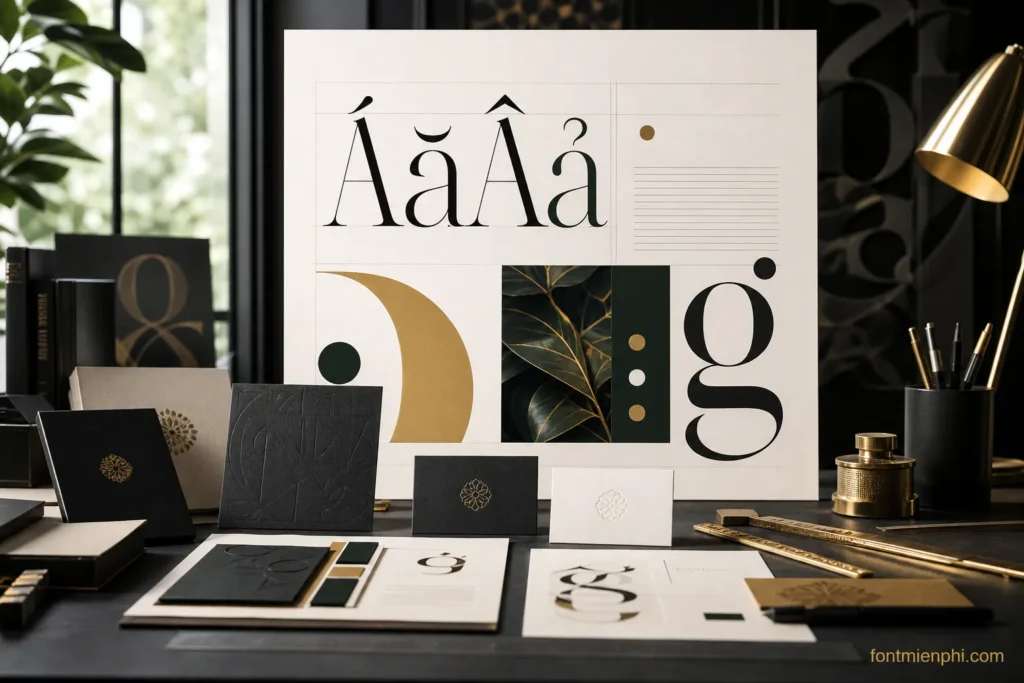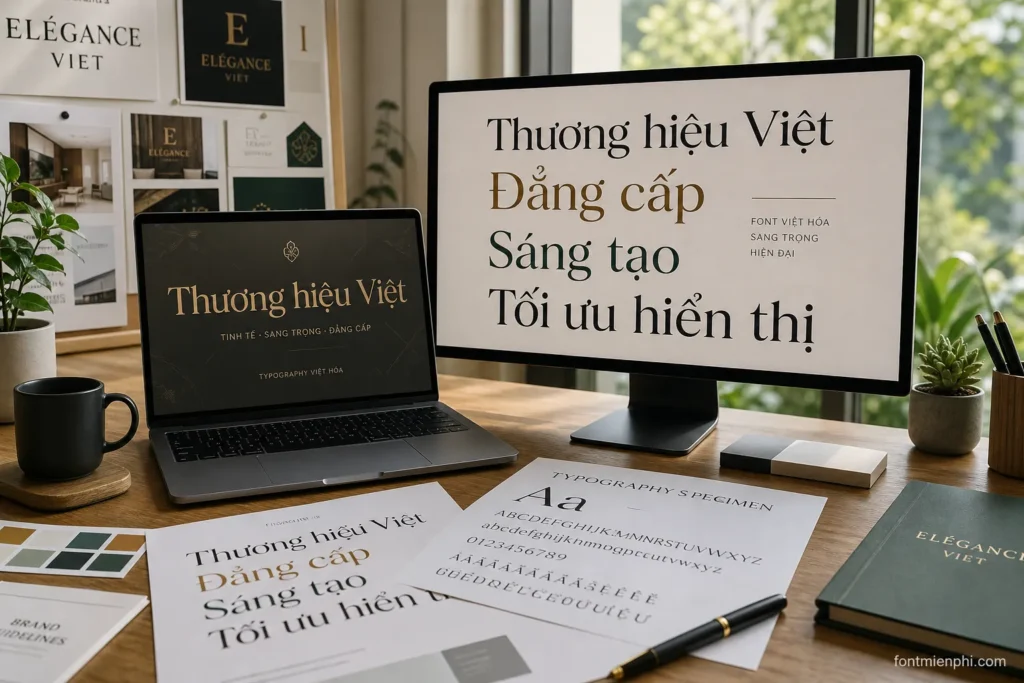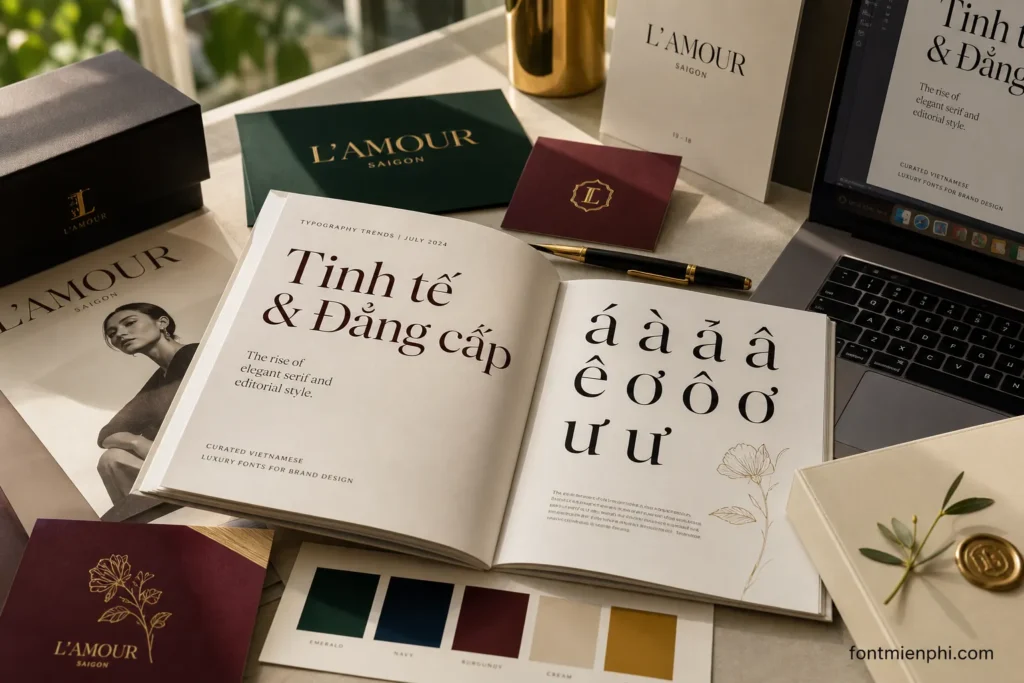
Xu Hướng Typography Tháng 7: Tổng Hợp Font Việt Hóa Sang Trọng Cho Thiết Kế Thương Hiệu
Tháng 7 đánh dấu sự trở lại mạnh mẽ của typography giàu cá tính, nơi các font Việt hóa sang trọng không chỉ làm đẹp bố cục mà còn định hình cảm nhận thương hiệu. Bài viết phân tích xu hướng chữ nổi bật, tiêu chí chọn font cao cấp và gợi ý nhóm font phù hợp cho logo, bao bì, website, hồ sơ thương hiệu và chiến dịch truyền thông.
Xu hướng typography tháng 7 trong thiết kế thương hiệu cao cấp
Typography trở thành ngôn ngữ nhận diện, không chỉ là phần chữ
Trong thiết kế thương hiệu hiện đại, typography không còn đóng vai trò phụ trợ cho hình ảnh. Kiểu chữ ngày càng trở thành một phần cốt lõi của hệ thống nhận diện, có khả năng truyền tải tính cách thương hiệu ngay cả khi chưa xuất hiện logo, màu sắc hay hình minh họa. Một thương hiệu mỹ phẩm cao cấp có thể tạo cảm giác tinh tế chỉ bằng một font serif thanh mảnh, trong khi một thương hiệu thời trang đương đại có thể gây ấn tượng bằng font display có cấu trúc táo bạo, khoảng cách chữ thoáng và tỷ lệ thị giác được kiểm soát kỹ.
Tháng 7 thường là thời điểm nhiều doanh nghiệp tái khởi động chiến dịch nửa cuối năm, chuẩn bị bộ sưu tập mới, làm mới bao bì hoặc nâng cấp hình ảnh trên nền tảng số. Vì vậy, xu hướng typography trong giai đoạn này thiên về tính ứng dụng cao: chữ phải đẹp khi xuất hiện trên bài đăng mạng xã hội, sắc nét trên website, đủ sang khi in trên hộp giấy, nhãn mác, menu, catalogue và vẫn giữ được khả năng đọc tốt với tiếng Việt có dấu.
Sự lên ngôi của serif thanh lịch và editorial style
Một trong những xu hướng nổi bật nhất của tháng 7 là sự trở lại của nhóm serif mang tinh thần editorial, lấy cảm hứng từ tạp chí thời trang, xuất bản cao cấp và các thương hiệu lifestyle quốc tế. Đặc trưng của nhóm này là nét tương phản cao, chân chữ sắc, dáng chữ có độ uyển chuyển vừa phải và cảm giác thị giác sang trọng. Khi được Việt hóa cẩn thận, các dấu thanh trong tiếng Việt không phá vỡ nhịp điệu chữ mà trở thành một phần tự nhiên của tổng thể.
Serif thanh lịch đặc biệt phù hợp với thương hiệu làm đẹp, nước hoa, trang sức, studio cưới, khách sạn boutique, nhà hàng fine dining và các nhãn hàng thủ công cao cấp. Khi dùng đúng cách, font serif giúp thương hiệu tạo cảm giác có chiều sâu, đáng tin cậy và giàu gu thẩm mỹ. Tuy nhiên, điểm cần lưu ý là không nên lạm dụng serif tương phản cao cho đoạn văn dài ở kích thước quá nhỏ, vì các nét mảnh có thể bị mất chi tiết trên màn hình độ phân giải thấp hoặc khi in bằng chất liệu không ổn định.
Sans serif sang trọng theo hướng tối giản nhưng không lạnh lùng
Bên cạnh serif, nhóm sans serif cao cấp cũng tiếp tục giữ vị trí quan trọng trong thiết kế thương hiệu tháng 7. Khác với phong cách sans serif công nghệ khô cứng, xu hướng mới ưu tiên các font có tỷ lệ cân bằng, đường cong mềm, độ mở chữ tốt và cảm giác thân thiện hơn. Đây là nhóm font phù hợp với những thương hiệu muốn thể hiện sự hiện đại, tinh gọn, chuyên nghiệp nhưng vẫn có cảm xúc.
Sans serif sang trọng thường được sử dụng cho hệ thống nhận diện cần tính nhất quán cao như website doanh nghiệp, ứng dụng, hồ sơ năng lực, landing page, bảng giá dịch vụ, tài liệu bán hàng và bao bì tối giản. Với tiếng Việt, chất lượng Việt hóa của sans serif thể hiện rõ ở dấu mũ, dấu móc, dấu hỏi, dấu ngã và khoảng cách giữa chữ có dấu trong tiêu đề lớn. Một font sans serif đẹp nhưng xử lý dấu kém có thể khiến bố cục mất cân bằng, đặc biệt khi thương hiệu thường xuyên dùng các từ như “thương hiệu”, “thiết kế”, “đẳng cấp”, “nghệ thuật” hoặc “chất lượng”.
Tiêu chí chọn font Việt hóa sang trọng cho thương hiệu
Khả năng hiển thị tiếng Việt có dấu là tiêu chí bắt buộc
Với thị trường Việt Nam, font đẹp chưa đủ; font phải hỗ trợ tiếng Việt chuẩn và hiển thị ổn định trong nhiều ngữ cảnh. Một bộ font Việt hóa chất lượng cần có hệ thống dấu cân đối, không bị chồng, không quá xa thân chữ và không tạo cảm giác nặng đầu ở các ký tự có nhiều dấu. Đây là yếu tố đặc biệt quan trọng với thiết kế logo, tiêu đề quảng cáo, bao bì sản phẩm và giao diện website, nơi chỉ một lỗi dấu nhỏ cũng có thể làm giảm đáng kể độ chuyên nghiệp của thương hiệu.
Khi đánh giá font Việt hóa, người thiết kế nên thử font bằng nhiều cụm từ có dấu phức tạp thay vì chỉ xem bảng mẫu chữ cơ bản. Các cụm như “đậm đà bản sắc”, “nghệ thuật thủ công”, “sản phẩm dưỡng thể”, “không gian sống tinh tế”, “thiết kế thương hiệu Việt” sẽ giúp kiểm tra độ ổn định của dấu, khoảng cách chữ và nhịp đọc. Nếu font vẫn giữ được sự hài hòa trong những cụm từ này, khả năng ứng dụng thực tế sẽ cao hơn nhiều.
Tính cách thương hiệu phải dẫn dắt lựa chọn kiểu chữ
Mỗi kiểu chữ mang một trường liên tưởng riêng. Serif tương phản cao thường gợi cảm giác sang trọng, cổ điển, thời trang hoặc nghệ thuật. Sans serif hình học tạo cảm giác hiện đại, sạch sẽ và có hệ thống. Script hoặc calligraphic mang lại nét cá nhân, mềm mại và thủ công, nhưng cần dùng tiết chế để tránh khó đọc. Display font tạo dấu ấn mạnh trong tiêu đề, poster hoặc logo, song không nên dùng đại trà cho toàn bộ nội dung thương hiệu.